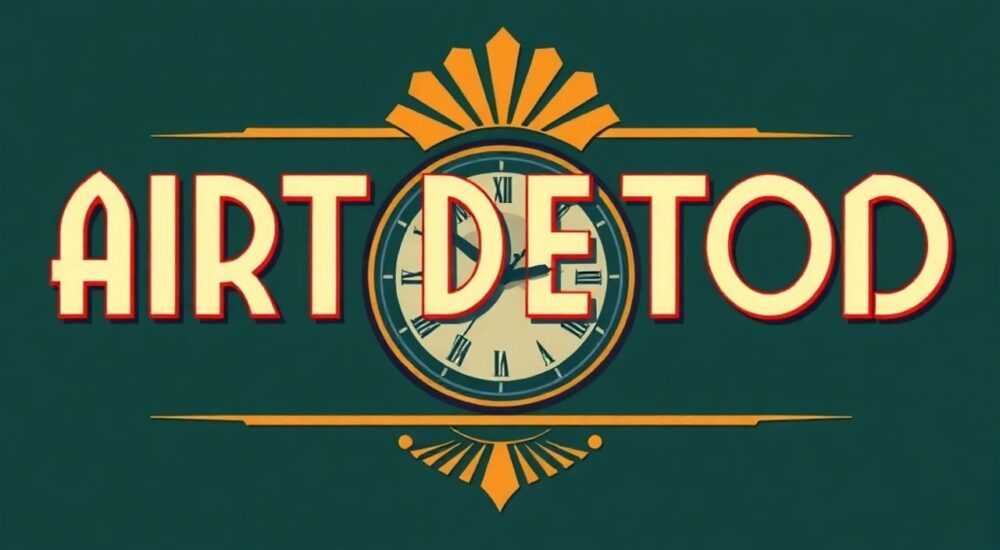
Шрифт ар деко
Шрифт ар деко представляет собой уникальное явление в истории типографики, которое продолжает вдохновлять дизайнеров и художников по сей день. Этот стиль возник на рубеже 1920-1930-х годов и стал символом эпохи модерна, роскоши и грандиозных перемен. Интересно, что даже спустя почти век, элементы этого стиля остаются актуальными в современном дизайне.
В этой статье мы подробно разберем историю возникновения шрифтов ар деко, их характерные особенности и основные принципы использования. Вы узнаете, как правильно применять эти шрифты в современных проектах, избежать распространенных ошибок и создавать действительно эффектные композиции.
Исторические корни ар деко в типографике
Ар деко зародился во Франции накануне Первой мировой войны, достигнув пика популярности в 1920-1930-х годах. Этот стиль стал отражением стремления общества к роскоши, технологическому прогрессу и новым формам искусства. В основе его лежали несколько важных культурных влияний: древнеегипетское искусство, ацтекские орнаменты, а также современные на тот момент достижения промышленности.
Интересно отметить, что развитие ар деко совпало с появлением новых технологий в полиграфии и рекламе. Это позволило дизайнерам экспериментировать с более сложными формами букв и создавать действительно уникальные шрифтовые композиции. Особенно активно этот стиль развивался в США, где он нашел свое воплощение в оформлении кинотеатров, рекламных плакатов и афиш.
Основные характеристики шрифтов ар деко
Шрифты ар деко отличаются рядом уникальных особенностей, которые делают их легко узнаваемыми:
- Геометричность форм и четкость линий
- Применение зеркальной симметрии
- Наличие характерных заостренных элементов
- Контраст между толстыми и тонкими штрихами
- Использование декоративных элементов
Одним из ключевых признаков является использование строгой вертикальной ориентации букв. Часто можно встретить характерные «ступеньки» в очертаниях символов, которые напоминают силуэты небоскребов. Цифры и буквы часто имеют треугольные или трапециевидные элементы, создающие ощущение динамики и движения.
Современное использование шрифтов ар деко
В современном дизайне шрифты ар деко находят свое применение в различных сферах. Они особенно эффективны для создания премиального образа бренда или продукта. Рассмотрим основные области применения:
- Ресторанный бизнес и гостеприимство
- Мода и ювелирные изделия
- Недвижимость класса люкс
- Развлечения и шоу-бизнес
При использовании шрифтов ар деко важно соблюдать баланс между декоративностью и читаемостью. Специалисты рекомендуют использовать их для заголовков и акцентных элементов, избегая набора больших текстовых блоков.
Типичные ошибки и рекомендации по их предотвращению
Многие дизайнеры допускают распространенные ошибки при работе со шрифтами ар деко:
- Использование слишком мелкого размера шрифта
- Перегруженность декоративными элементами
- Неправильное сочетание с другими шрифтами
- Избыточная цветовая насыщенность
Чтобы избежать этих проблем, следуйте простым правилам:
Проверьте себя:
- Правильно ли вы выбрали контраст между текстом и фоном?
- Не перегружаете ли вы композицию деталями?
- Соблюдается ли общая гармония дизайна?
Перспективы развития и новые технологии
Современные технологии открывают новые горизонты для шрифтов ар деко. Появление переменных шрифтов (Variable Fonts) позволяет создавать адаптивные варианты, которые могут менять свои параметры в зависимости от контекста использования. Это особенно важно для цифровых медиа, где требуется высокая гибкость в отображении.
Важным направлением развития является также создание многоязычных версий шрифтов, поддерживающих различные письменности. Это расширяет возможности использования ар деко в глобальных проектах и международных кампаниях.
- «Важно помнить, что ар деко – это не только прошлое, но и настоящее. Стиль постоянно эволюционирует, адаптируясь к новым условиям.»
- «Успешное использование шрифтов ар деко требует глубокого понимания их природы и возможностей.»